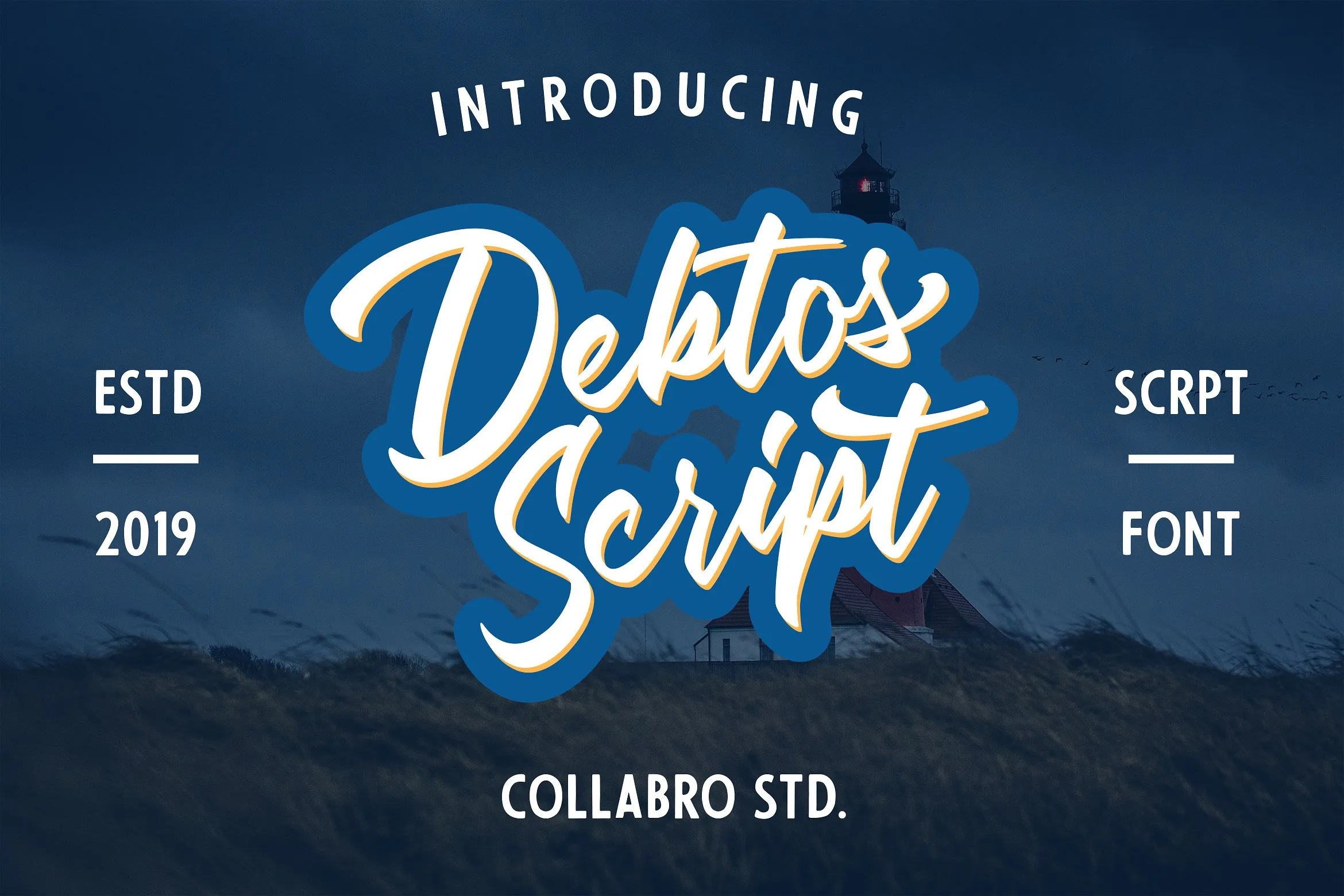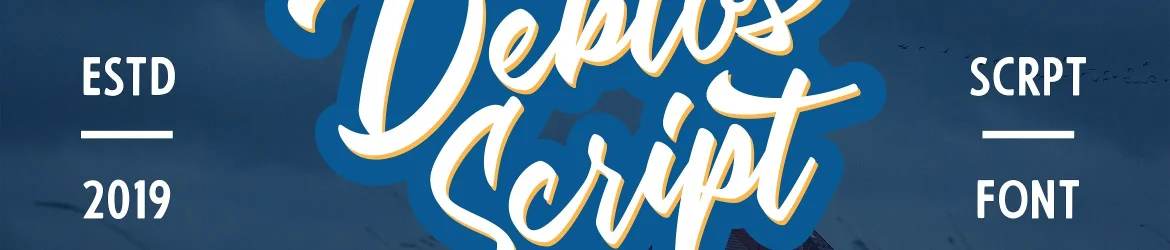
Debtos Script Font – Download Grátis
Este é um script elegante que transmite uma sensação casual e sofisticada. A Debitos Script Font é um estilo de letra desenhado a mão inspirado em posters clássicos, com linhas monolineares e curvas únicas. Ela tem um fluxo elegante e fluido, como se fosse traçado diretamente do papel para o monitor. Essencialmente uma fonte de exibição feita por mãos humanas, ela contém todas as letras maiúsculas e minúsculas, números e pontuação, além de muitas variações em cada caracter. Entre essas variações encontramos alternativas de opentype, ligaturas comuns e até mesmo algumas swash para que você possa personalizar seus designs conforme necessário. Este é um ótimo recurso para logos, carimbo, cartazes, design de roupas ou etiquetas. Debitos Script Font não só oferece uma apresentação única e diferenciada da sua marca como também permite uma maior flexibilidade na criação de design, dando-lhe a liberdade para expressar seu estilo pessoal. Seja para um logotipo impecável para usar em materiais impressos ou para criar um look único no design gráfico, Debitos Script Font certamente se tornará um dos seus novos favoritos na sua biblioteca de fontes.